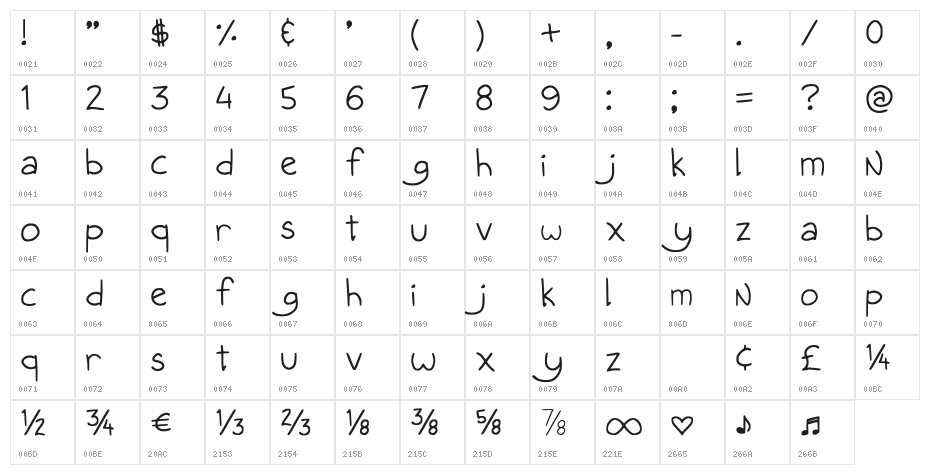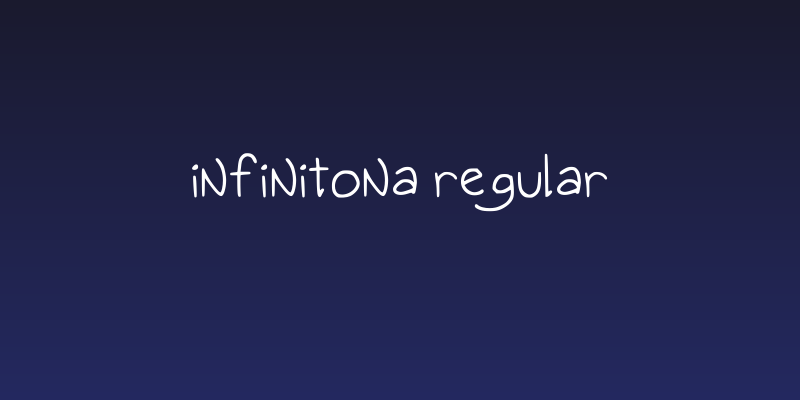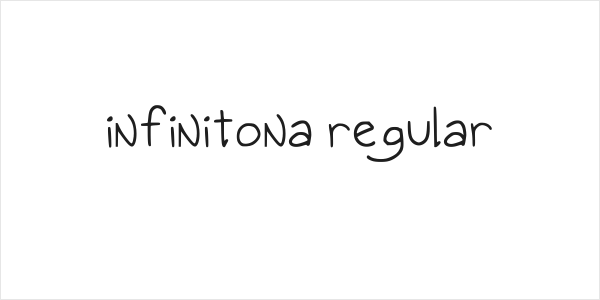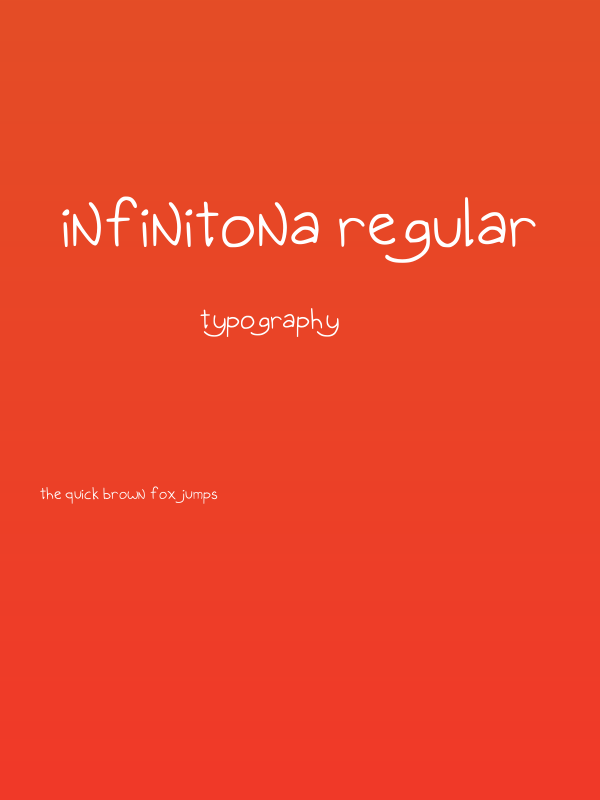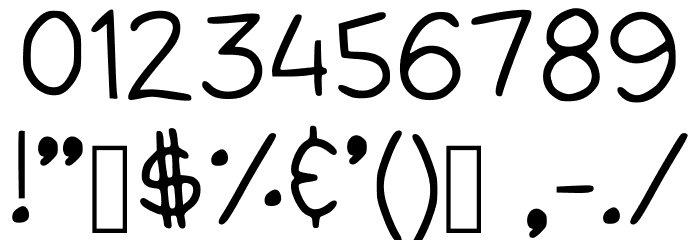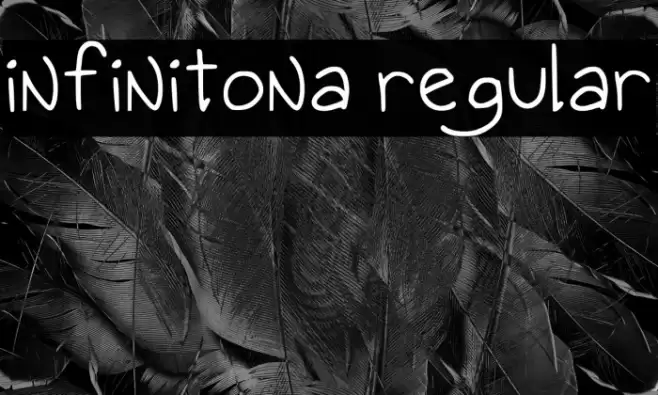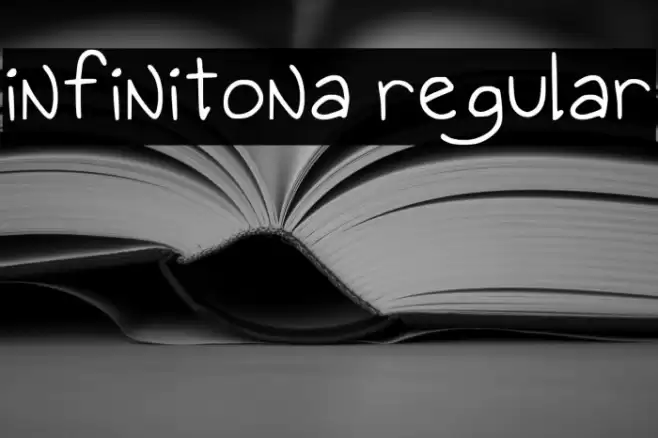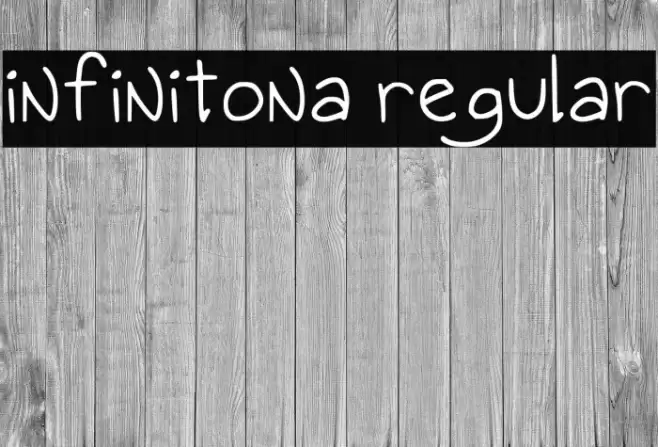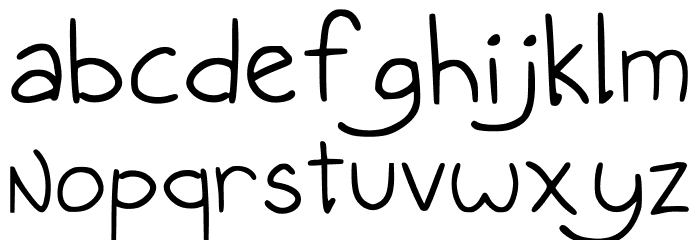
Infinitona Regular Font
| フォントファミリー | Infinitona |
| 全体的なスタイル | Casual |
| 用途 | Headlines, Logos, Informal Text |
| おすすめプロジェクト | Ideal for children's books, casual invitations, greeting cards, and playful branding projects. |